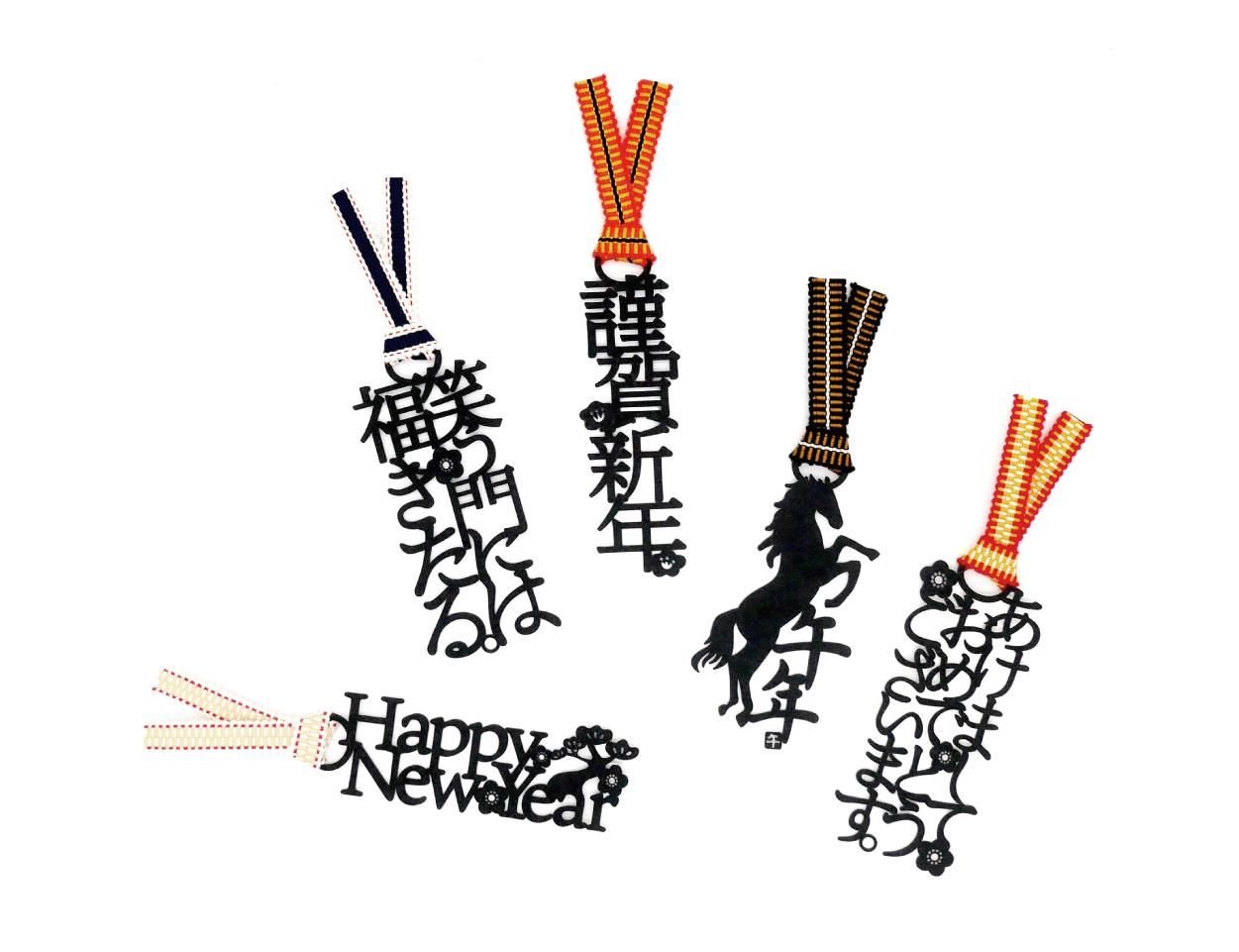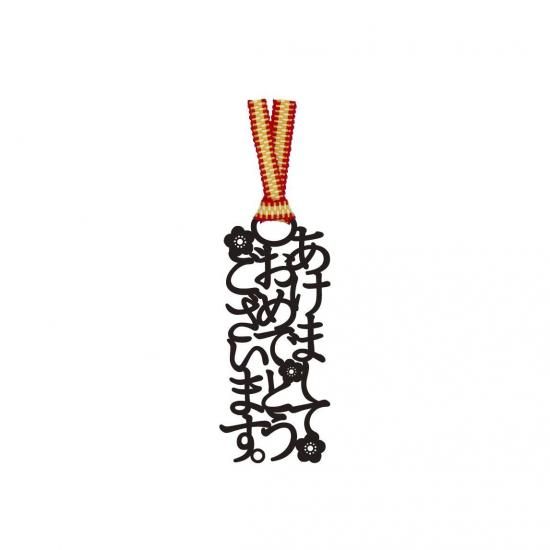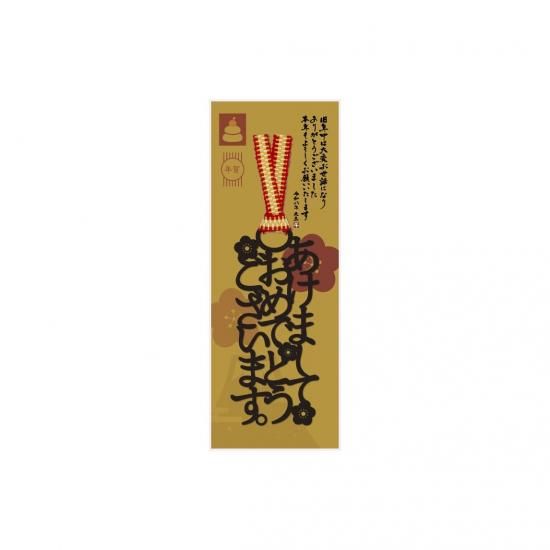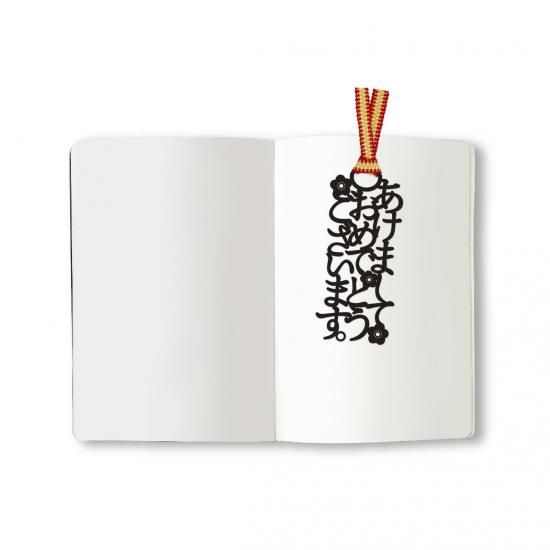
【年末年始限定】文字のあけおめのしおり「あけましておめでとうございます」
もーいーくつねーるーとー♪
文字のお正月のしおり♪
新年、もう少しであけましておめでとうございます!
新しい年を迎えるにあたり、特別なアイテム『文字のお正月のしおり』をご紹介します!
お正月らしい華やかなデザインで、新年の始まりを彩ります。
文字の謹賀新年のしおり「謹賀新年」
文字のあけおめのしおり「あけましておめでとうございます」
文字のHappy New Yearのしおり「Happy New Year」
文字の笑う門にはのしおり「笑う門には福来たる」
文字の干支のしおり「未年」
日本のお正月といえば、家族や友人との再会、縁起物を飾る楽しみがありますよね。
『文字のお正月のしおり』は、そんな伝統や文化に敬意を込めつつ、現代風にアレンジした気持ちがほっこり温かくなるコミュニケーションツールです。年始のご挨拶や、ちょっとしたプレゼントにおすすめです。
また、『文字のお正月のしおり』は、ビジネスシーンでもその魅力を発揮します。
お取引先さまへの新年のご挨拶回りは、恒例行事のひとつです。
日頃の感謝の気持ちを伝える際に、『文字のお正月のしおり』を添えることで、取引先や顧客との関係をより強固にするきっかけに。松の内(1月7日または15日まで)の期間中にお渡しすることで、新年の縁起を担ぎつつ、印象的なご挨拶を演出できます。贈る側のスペシャルが伝わる『文字のお正月のしおり』は、名刺などに添えるだけで、ビジネスの場でも一目置かれるアイテムになること間違いなしです。